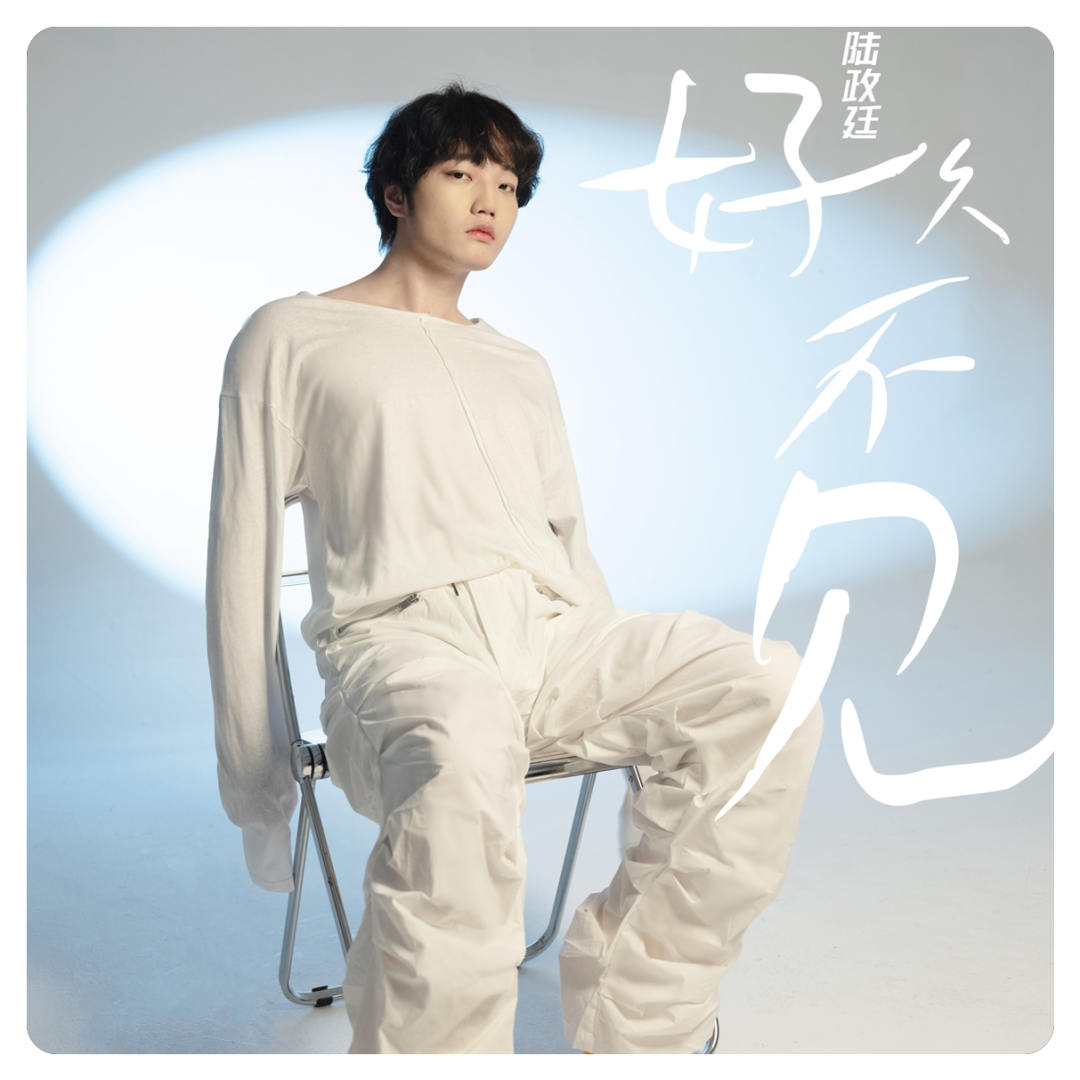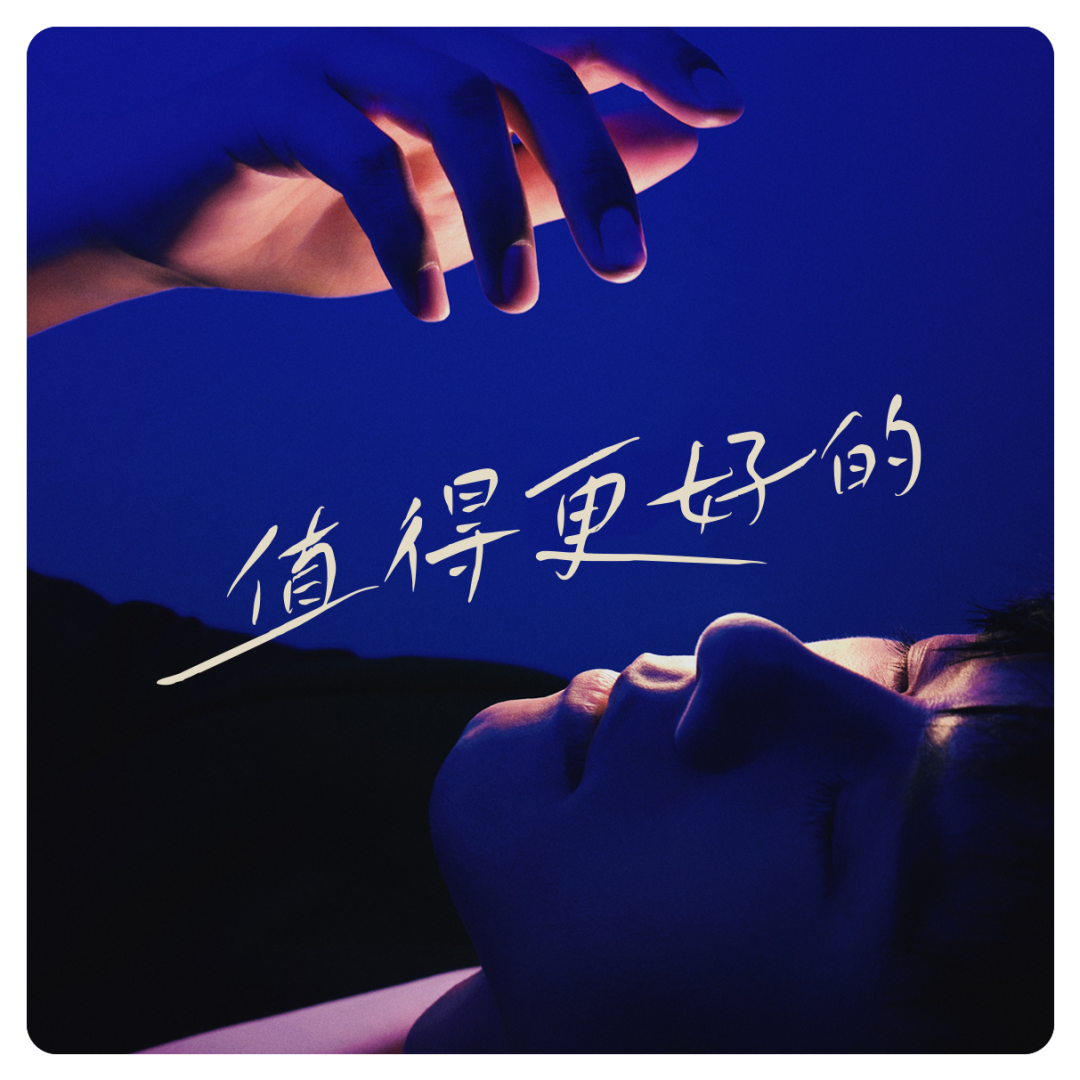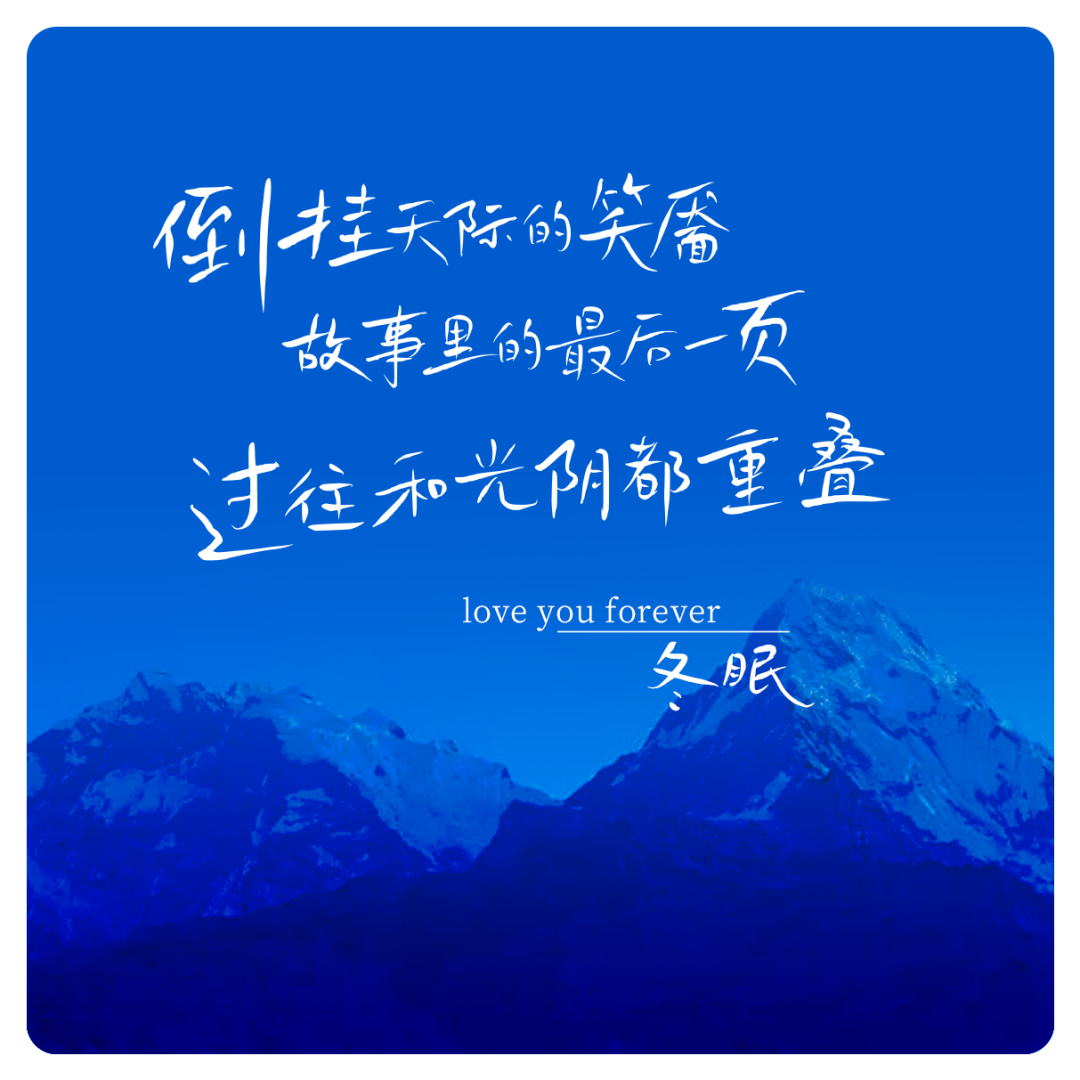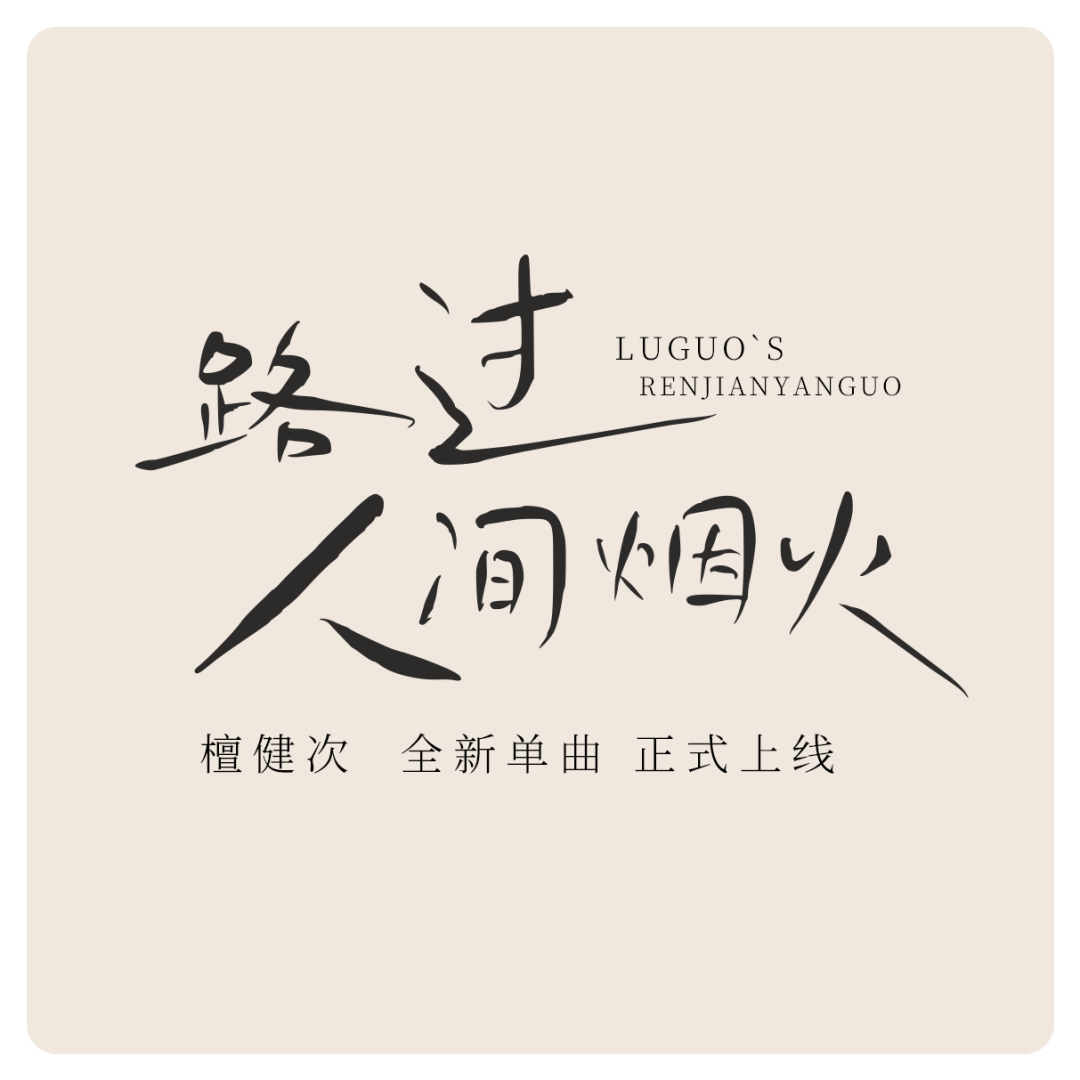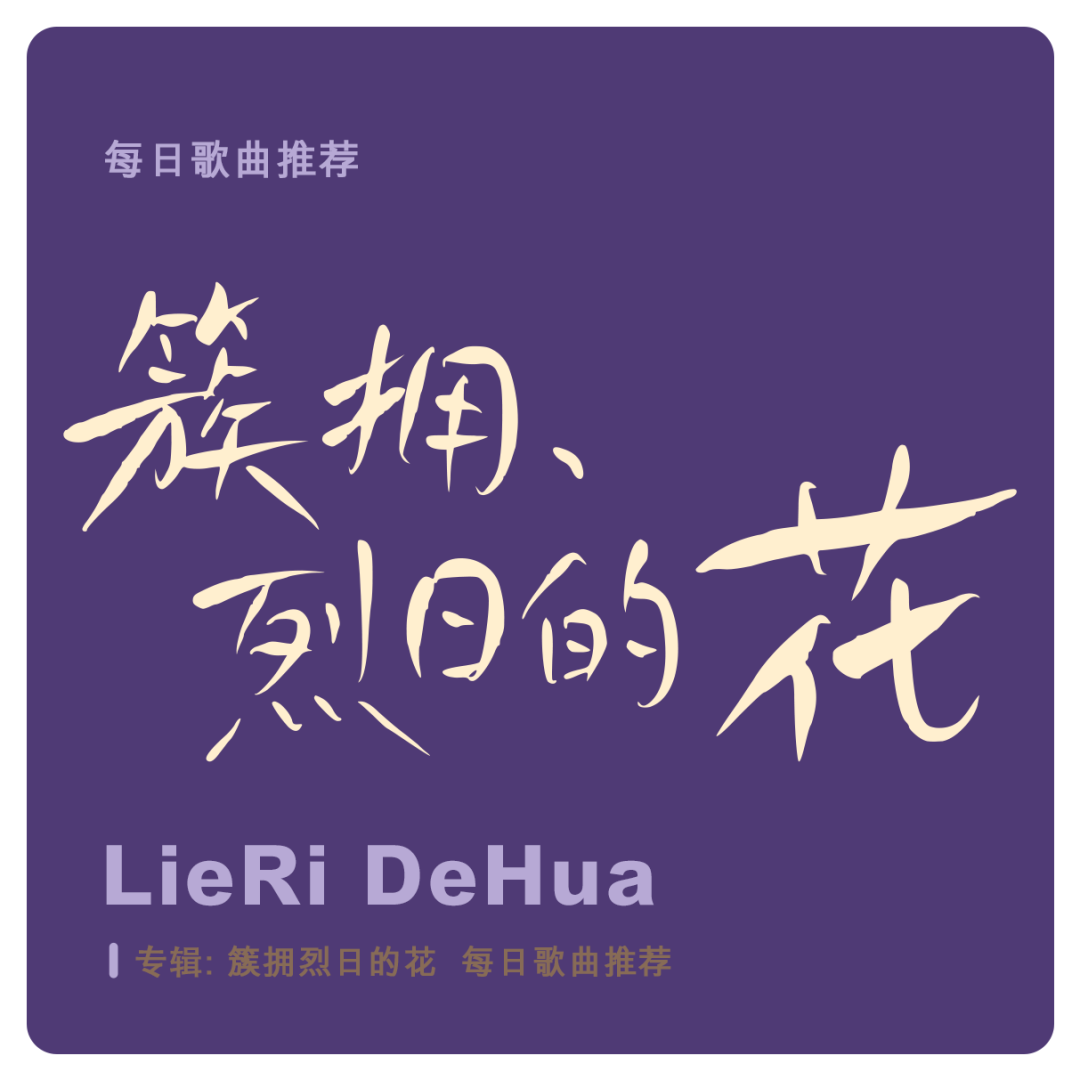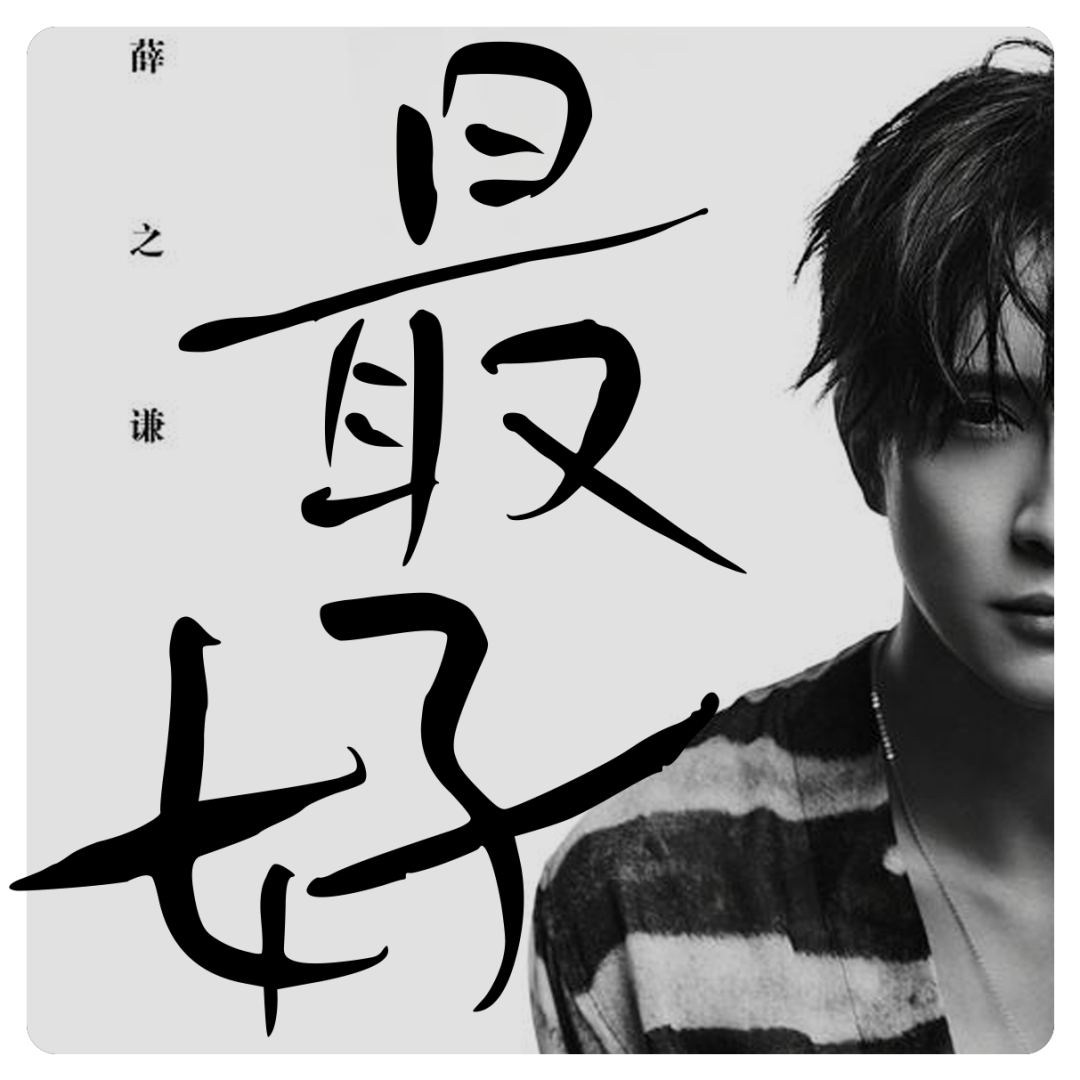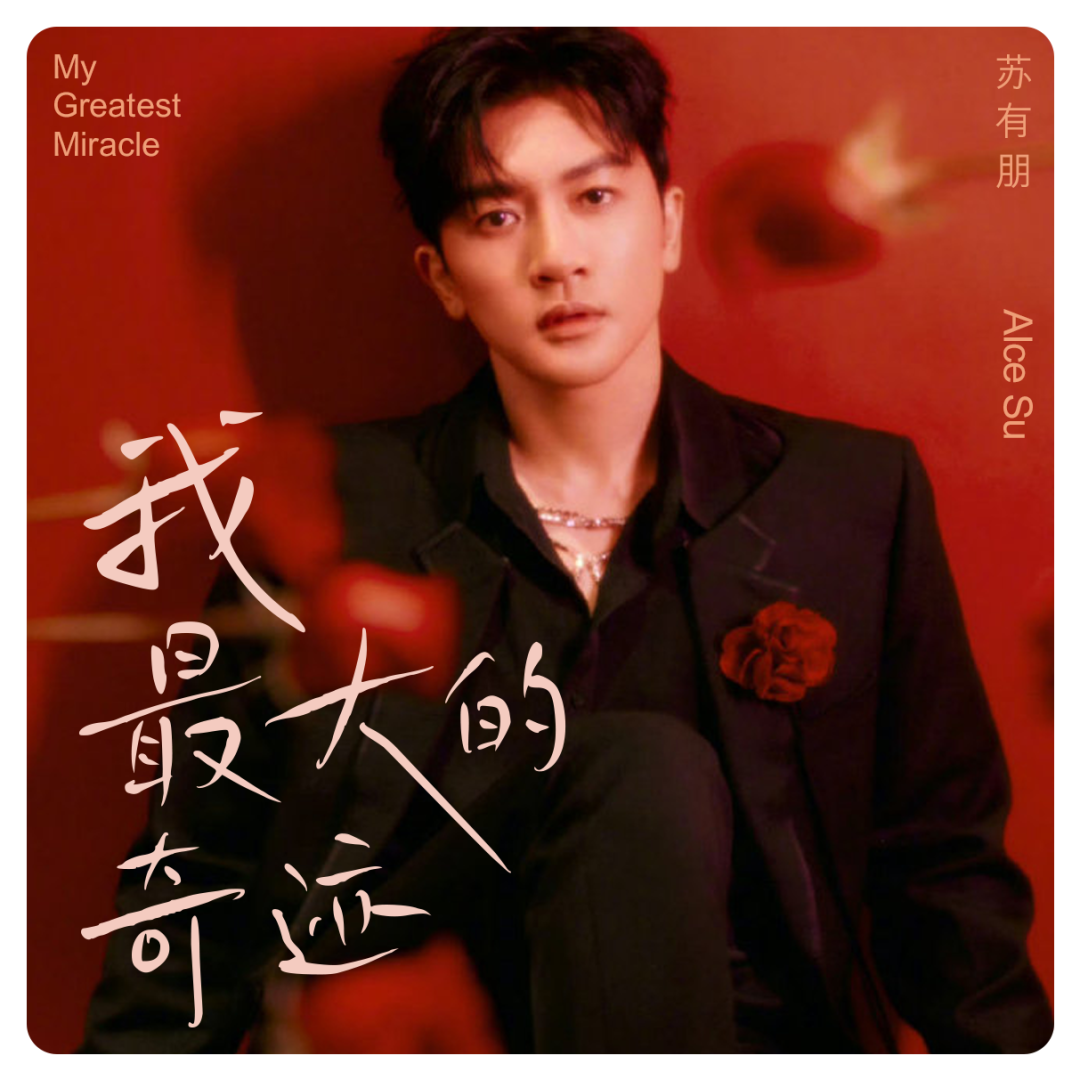
关于这套鸿雷拙书简体被我遗弃,又被我从回收站里捡回来的字体|再丑也有用武之地(免费商用)
关于这套被我从回收站捞起来的字体简单说两句
这套字体写于2021年6月份
命名为《鸿雷拙书简体》
拙的本意就是拙略,“丑”的意思,因为写完后才发现是真的丑,放在文件夹里一年半了,前几天整理文件的时候没有任何犹豫直接被我删了。
然而前几天有个客户发了几张图给我,问我海报上面的字体会写吗。
于是我想到刚被我删掉不久的一套字体,我捡回来,敲上几个字发给他,意外的是居然通过了。
突然发现字体本身也许跟人一样,无论好坏美丑,都有人喜欢,毕竟每个人审美不同,没办法做出一款人人都喜欢的字体,字体的多样性本来就是为了适应多样性的应用场景。
从回收站捡回来后简单的P了几张图看看效果,感觉也还不错,就当提前完成今年的一个flag吧,2023完成个人的第三套免费字体。前两套分别是《鸿雷板书简体》发布于2020年4月,以及《鸿雷行书简体》发布于2022年8月。
今天这里正式发布个人第三套手写字体《鸿雷拙书简体》